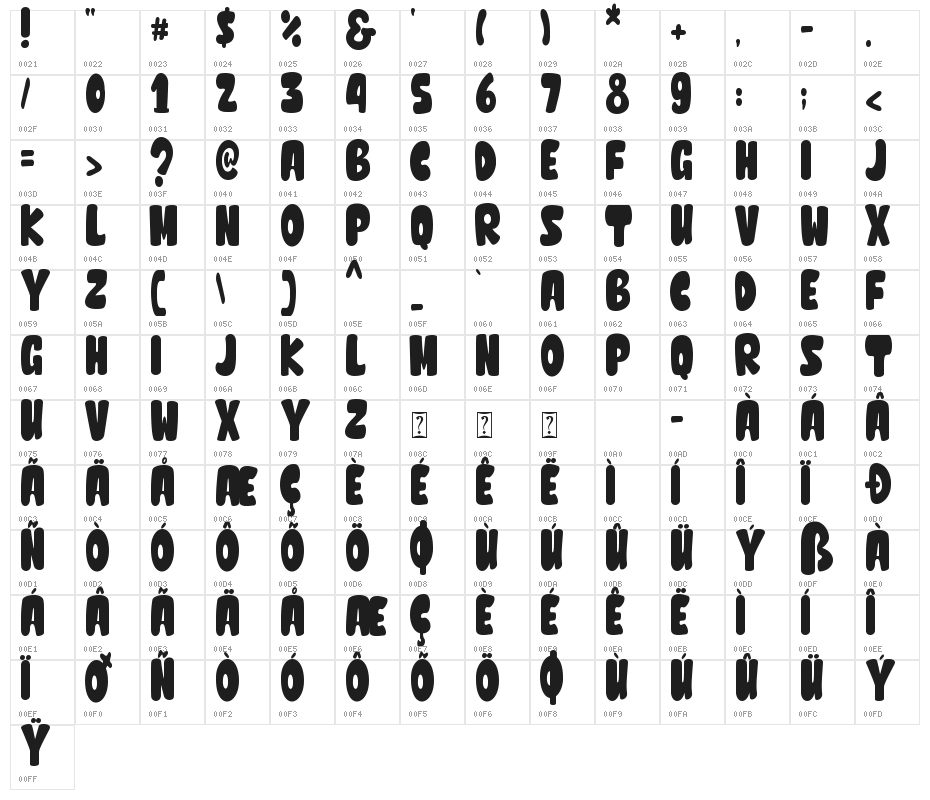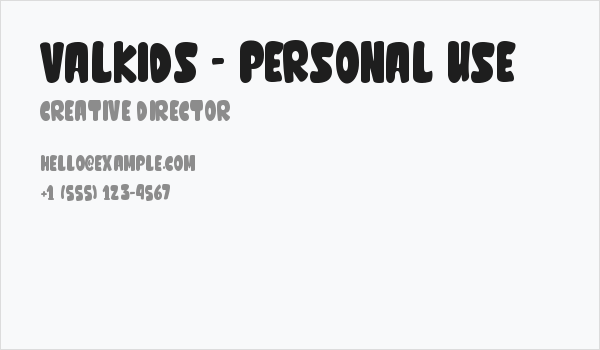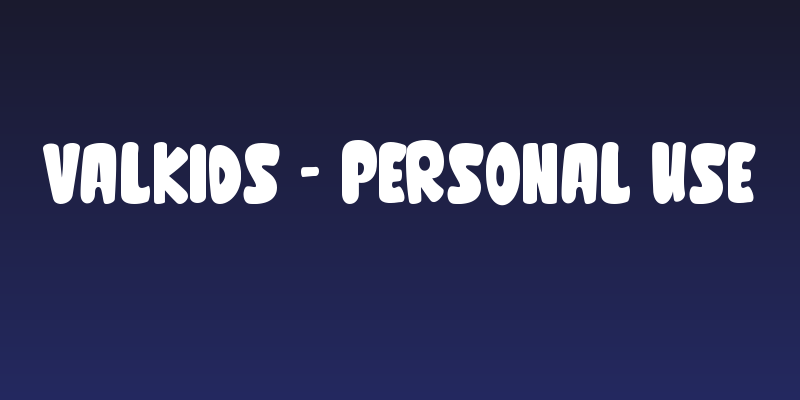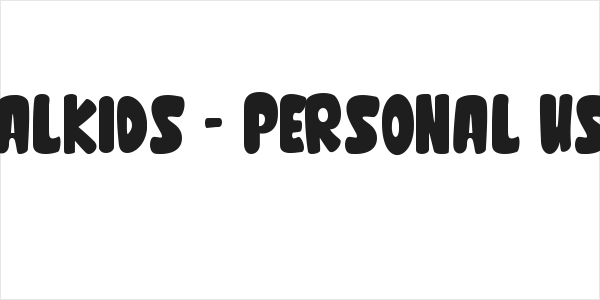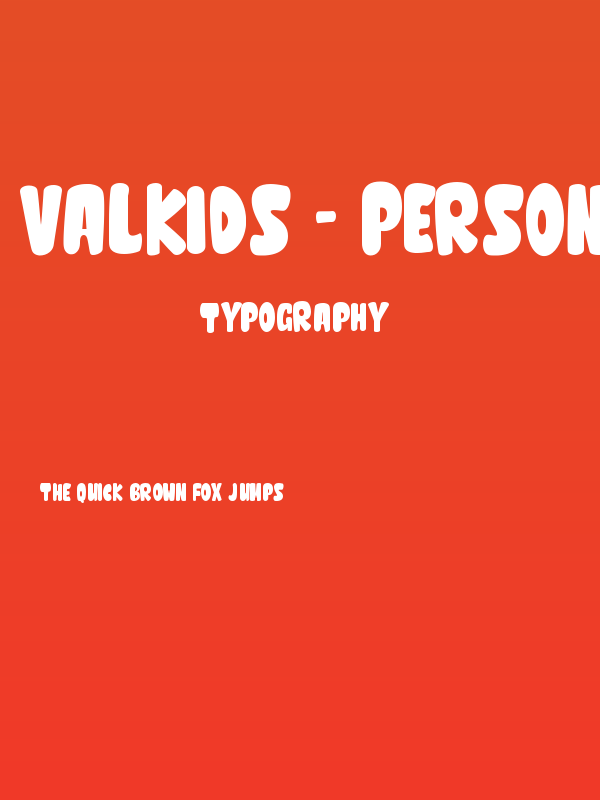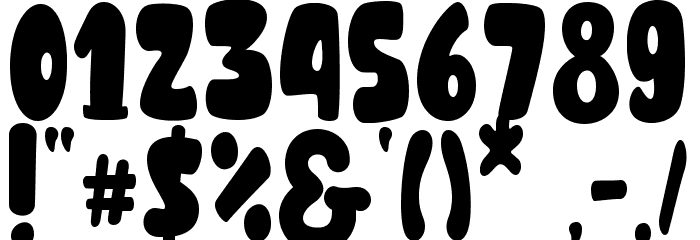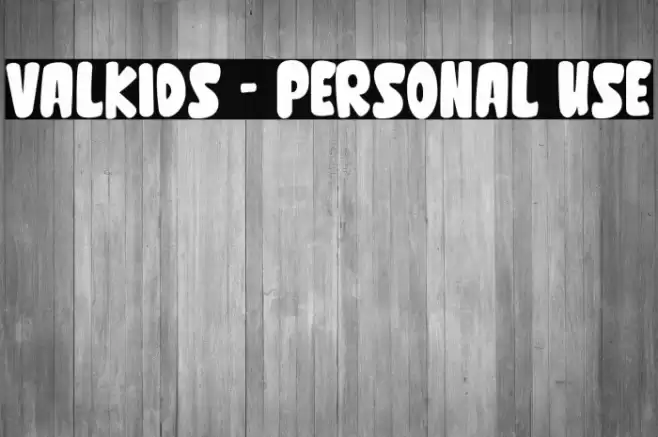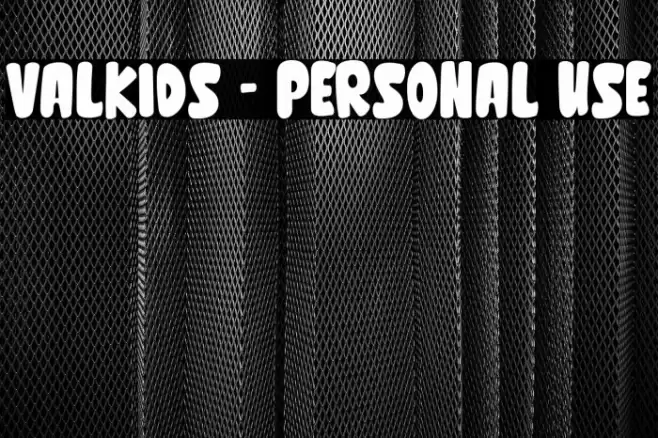
Valkids - Personal use Font
Fonts by Letterara
| النمط العام | Playful, Fun, Whimsical |
| حالة الاستخدام | Headlines, Posters, Branding |
| مشاريع مقترحة | Ideal for children's books, playful branding, posters, and creative projects that require a fun and engaging typeface. |